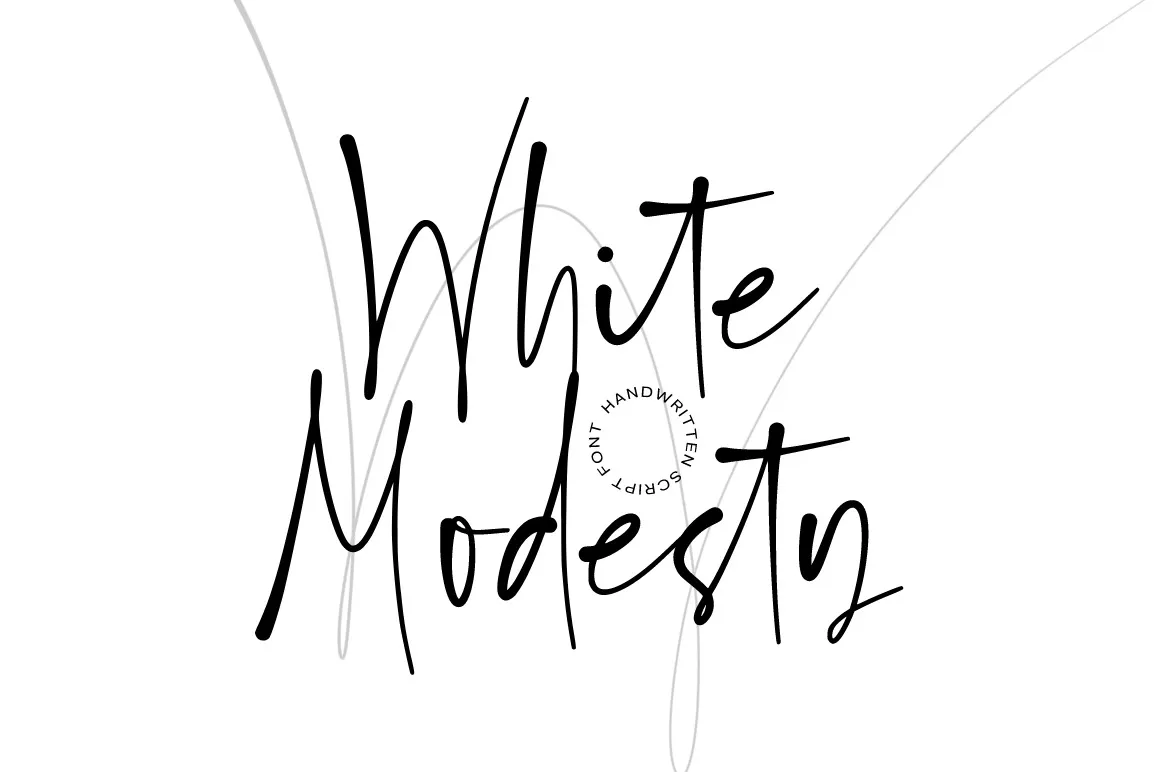
White Modesty Font – Fonte Grátis
White Modesty Font
Esta é uma fonte script delicada e elegante, criada pelo designer Tedyindrawan. Sua natureza fluida e elegante tornam-a perfeita para complementar um vasto leque de estilos. Perfeito para assinaturas, marcações, logotipos, moda, cartões de visitas, fotografia, capas, mídia social, citações, e qualquer outro projeto que necessite da adição de uma tocha humilde. Sua característica principal é o seu conjunto atraente e casual de caracteres. Isso permite que se adapte facilmente para diversos estilos e formatos, criando um impacto imediatamente visível em cada design onde ela é usada. O resultado é um resultado visual incrivelmente belo, com uma aparência deslumbrante tanto no papel quanto na tela. A fonte White Modesty foi projetada especificamente para aqueles que buscam um estilo minimalista e sofisticado. É uma opção ideal para quem quer incorporar um toque autêntico de escrita a seus trabalhos, seja eles digitais ou impressos. Seja no ambiente de trabalho, em publicações pessoais ou mesmo nas mídias sociais, ela é uma escolha perfeita que destaca sua criatividade e individualidade.